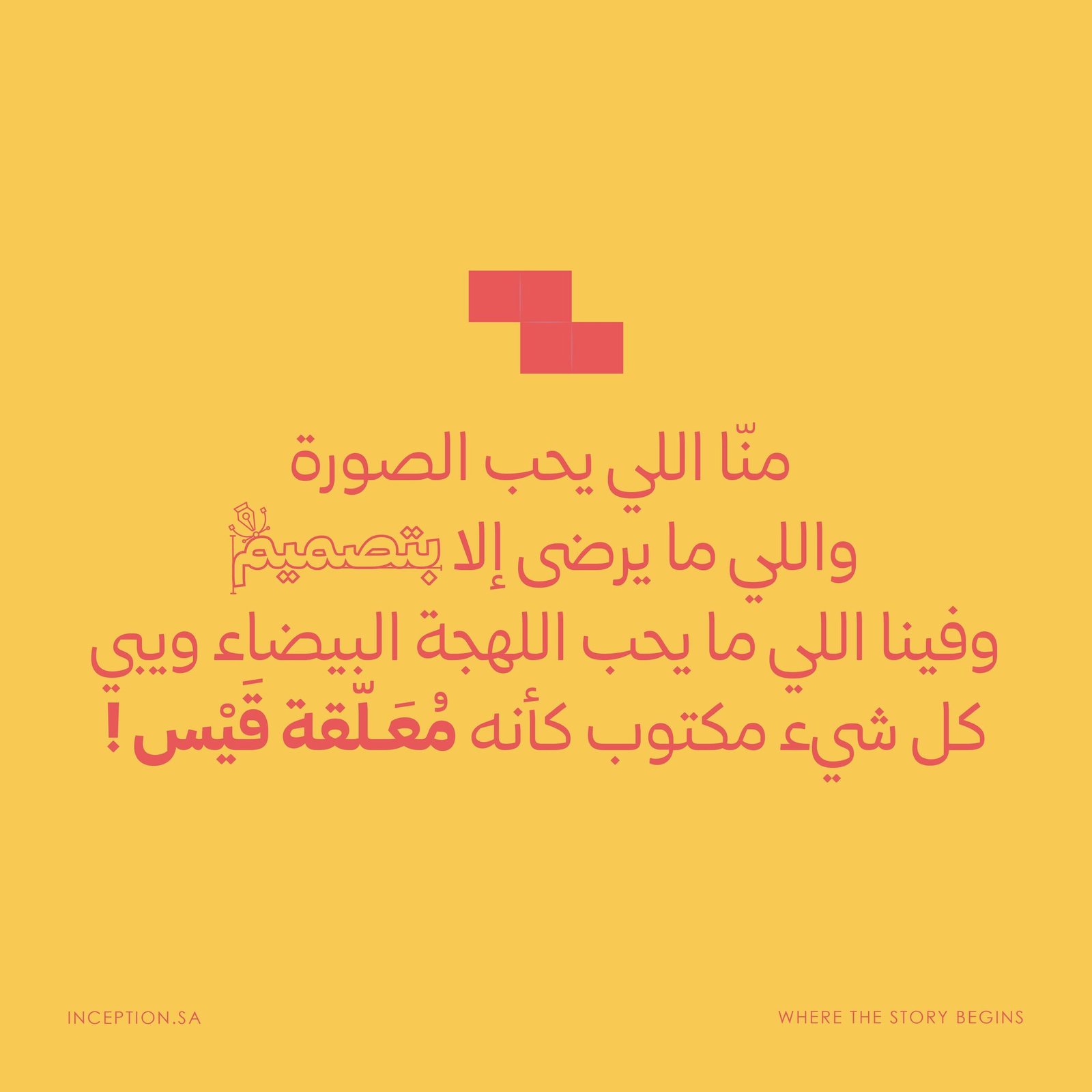
استخدام خط زاجل – inception
خط نسخ عربي حديث وأنيق يتميز بتصميمه العصري الذي يجمع بين الزوايا والانحناءات، مما يمنحه مظهرًا مميزًا. كما يدعم العديد من مزايا Open Type، مما يجعله خيارًا مثاليًا للاستخدام في مجموعة متنوعة من التطبيقات.يدعم خط زاجل اللغة العربية فقط، مما يجعله خيارًا مثاليًا للمشاريع العربية. ويمكن استخدامه في تصميم الجرافيك، والكتابة المطبوعة، والويب، والتطبيقات المحمولة.